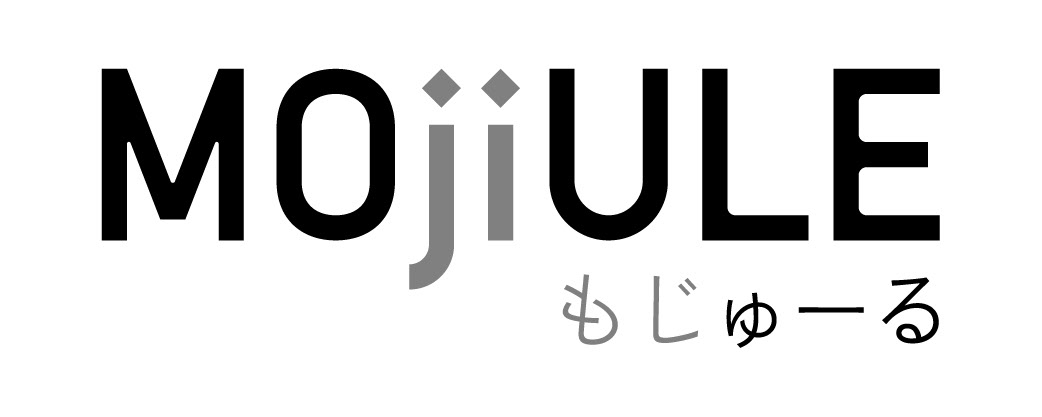
「MOjiULE(もじゅーる)」
ひらがなを構成するパーツを「ひらがなの素( もと) 」と呼び、タイピングによりひらがなの素から「ひらがな」を再構築するインタラクティブ作品です。下のボタンから実際に体験できます。※PC環境でのみ動作します。
CONCEPT
「は」と「ほ」や「め」と「ぬ」のように「似た形状のひらがながある」という認識を表面化する事で、普段意識していなかった面白さを発見させ、慣れ親しんだ文字への新たな魅力を感じられると考えました。そこで、ひらがなの「パーツ」に着目しひらがな同士で複数のパーツを共有する作品を制作しました。
TITLE
「基本の構成要素」を意味する「モジュール(module)」と「文字」を掛け合わせて、「MOjiULE(もじゅーる)」と名づけました。
FONT DESIGN
「ひらがなの素」は全部で22 種類。この22 種類のパーツからおよそ100 の文字が再現可能です。フォントは個々のパーツが複数のひらがなで用いられることを意識し美しく汎用的なパーツになるよう1から設計しました。